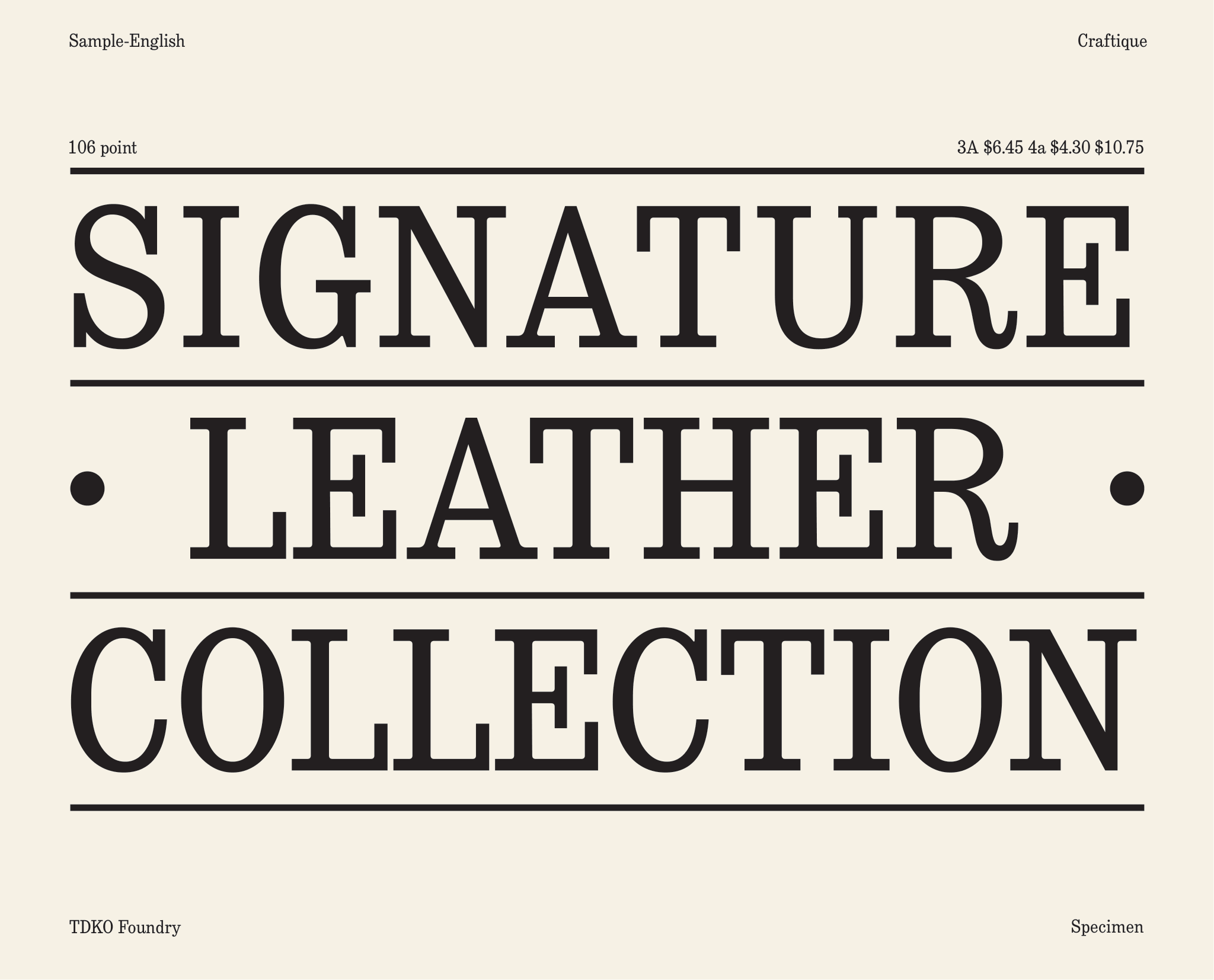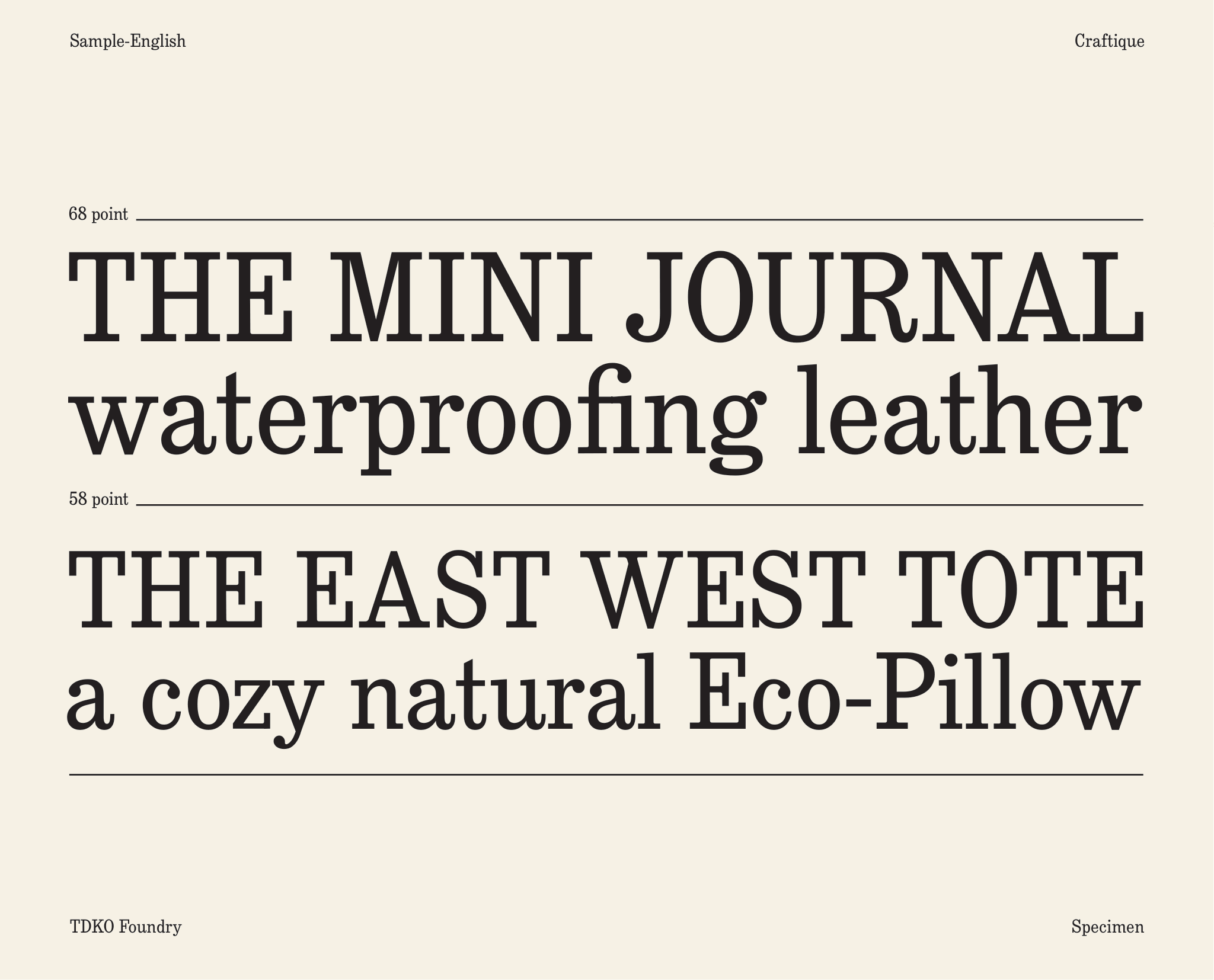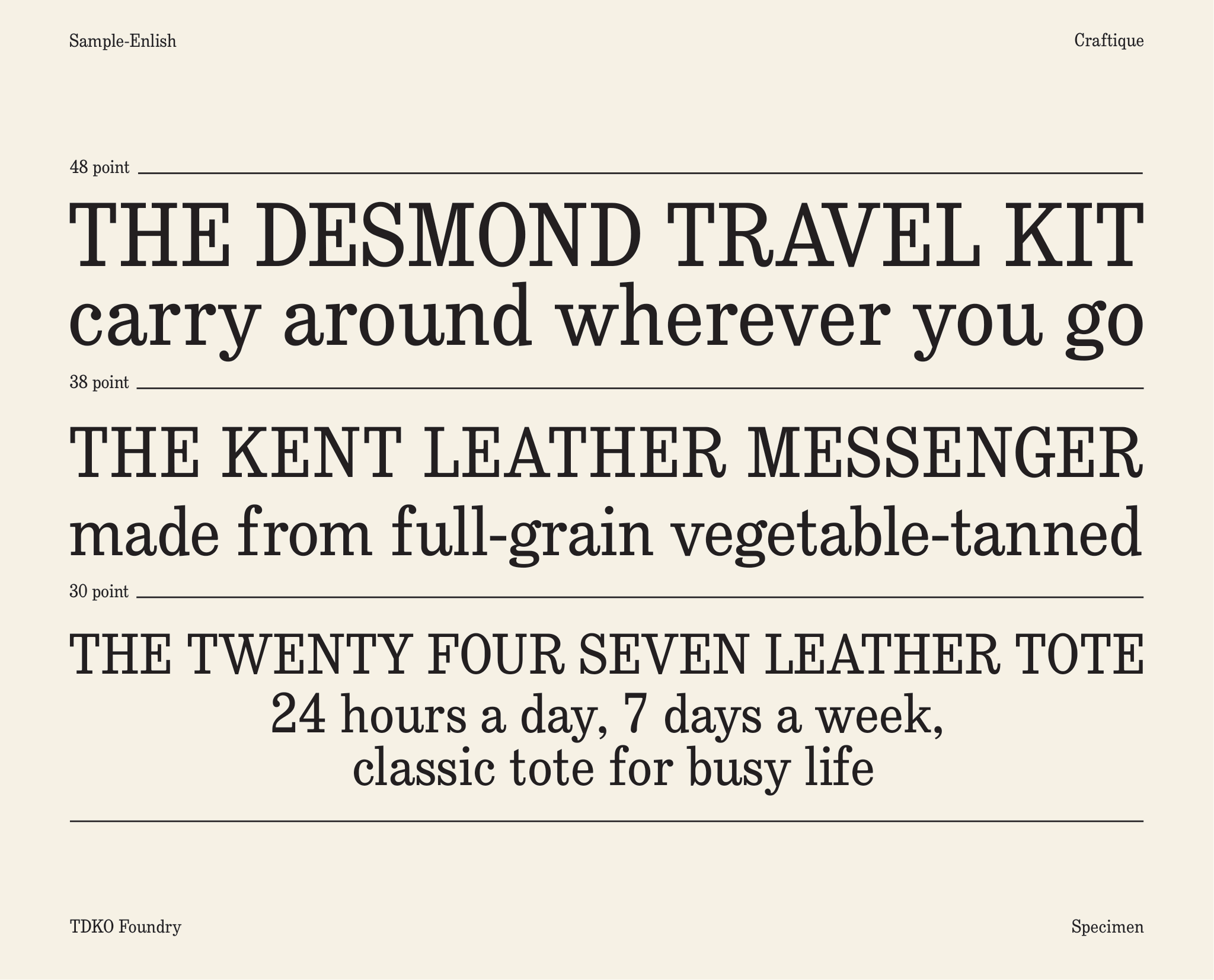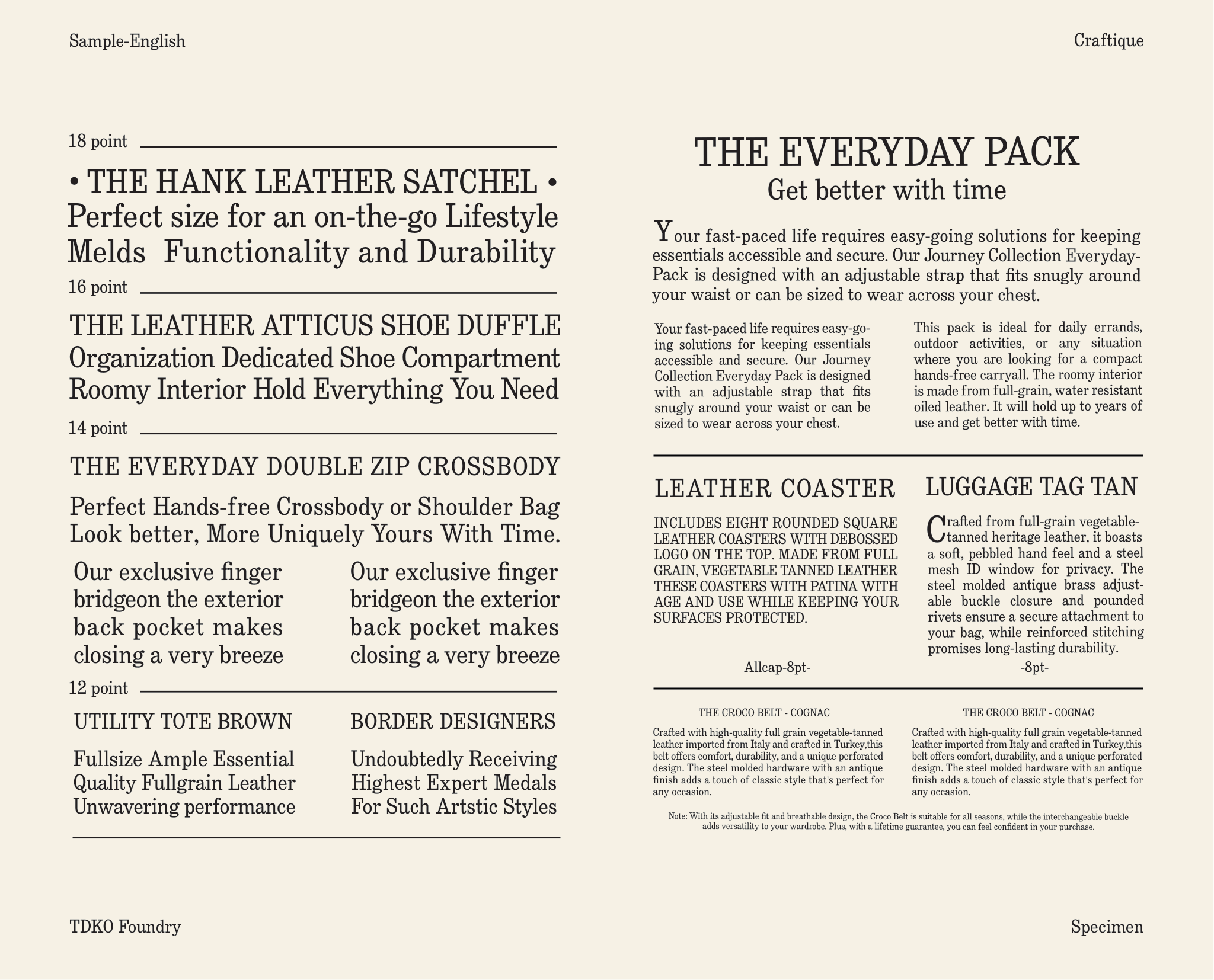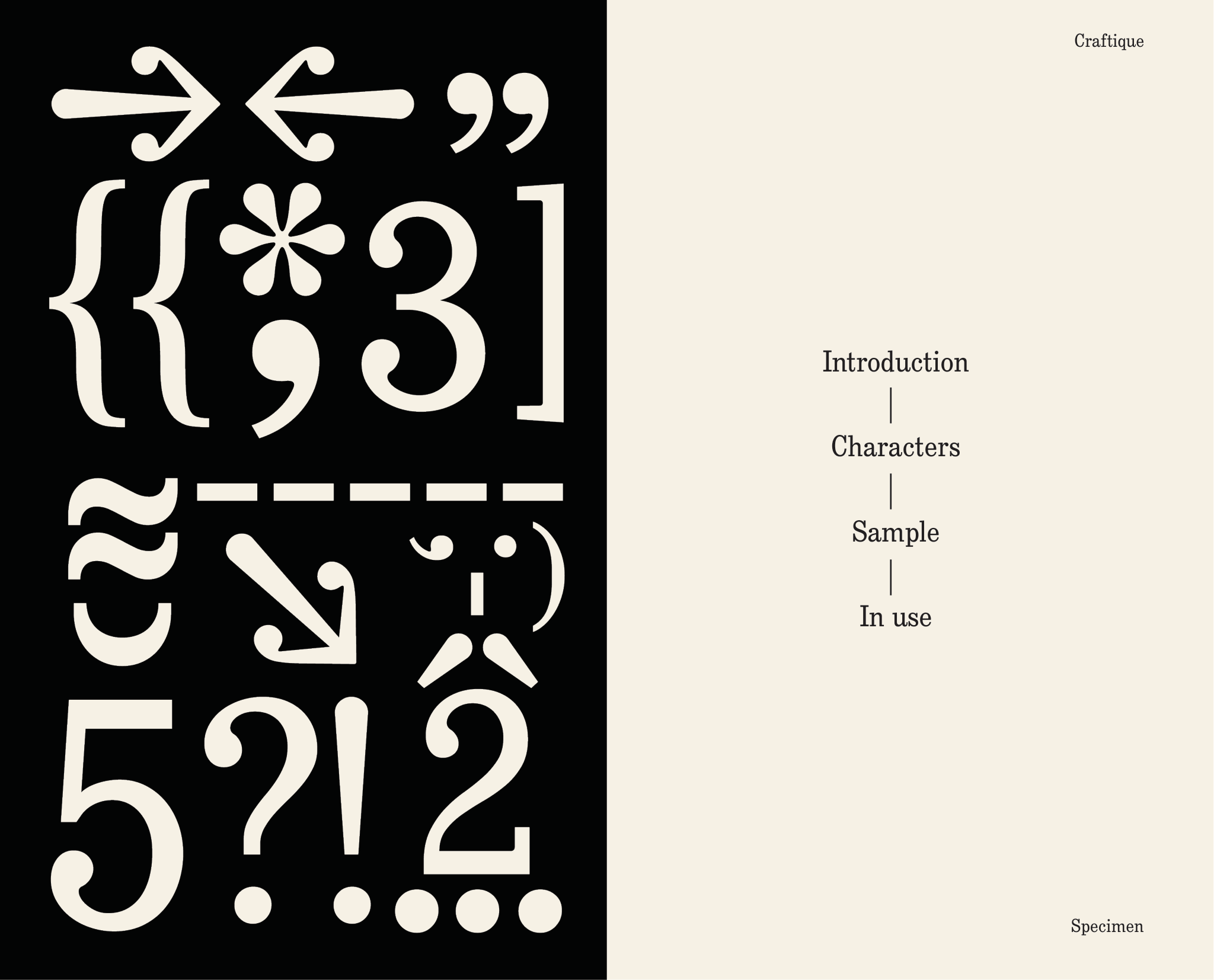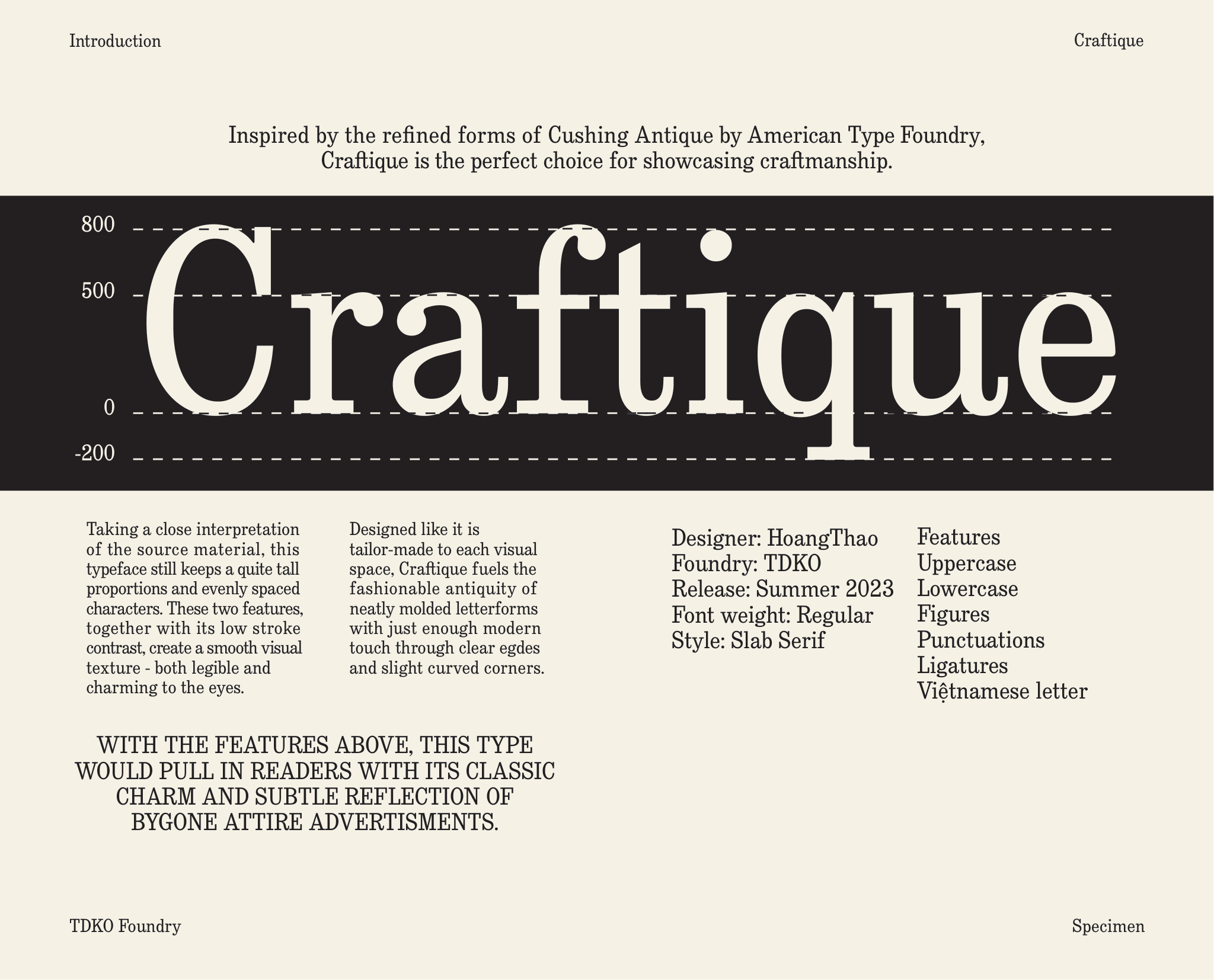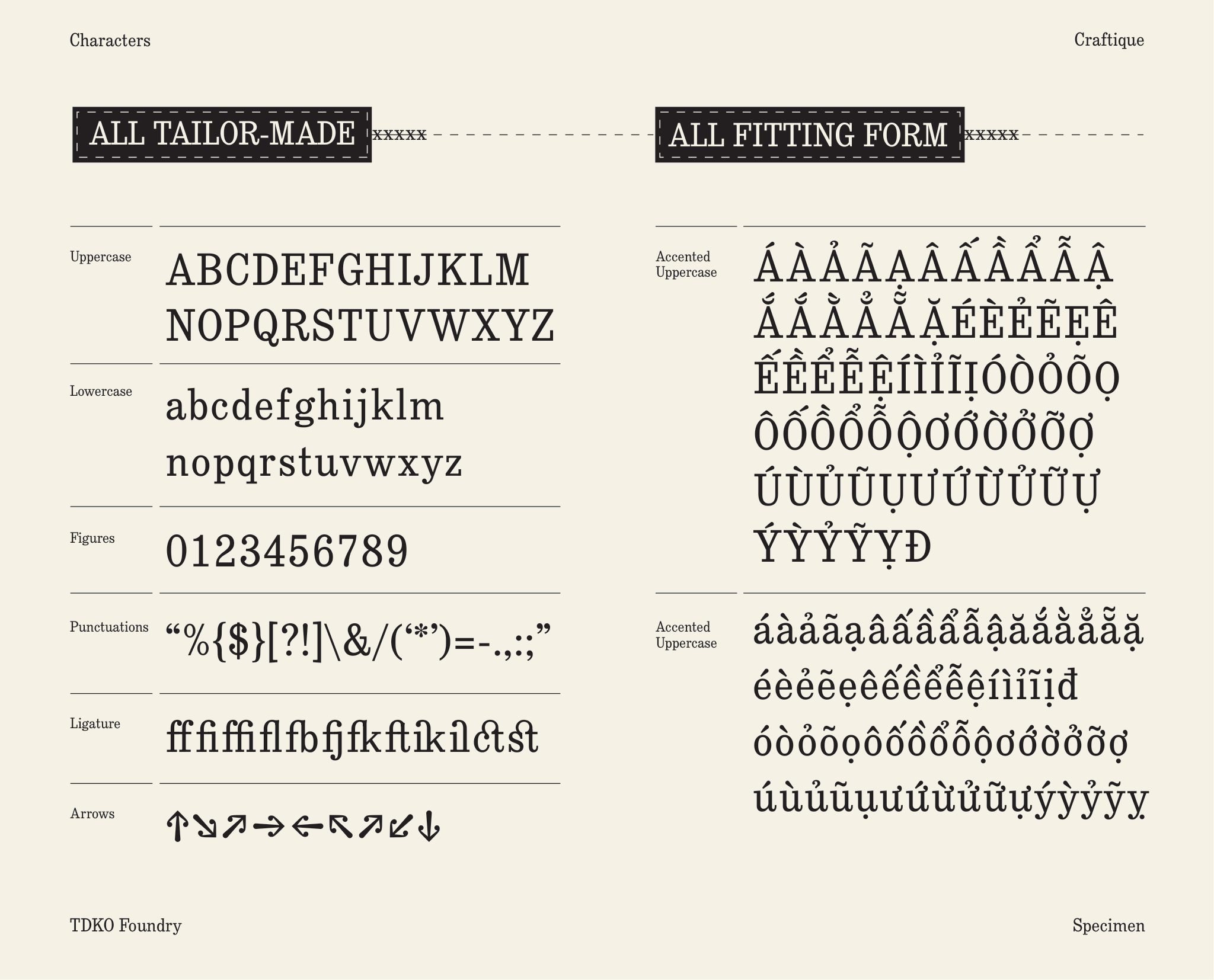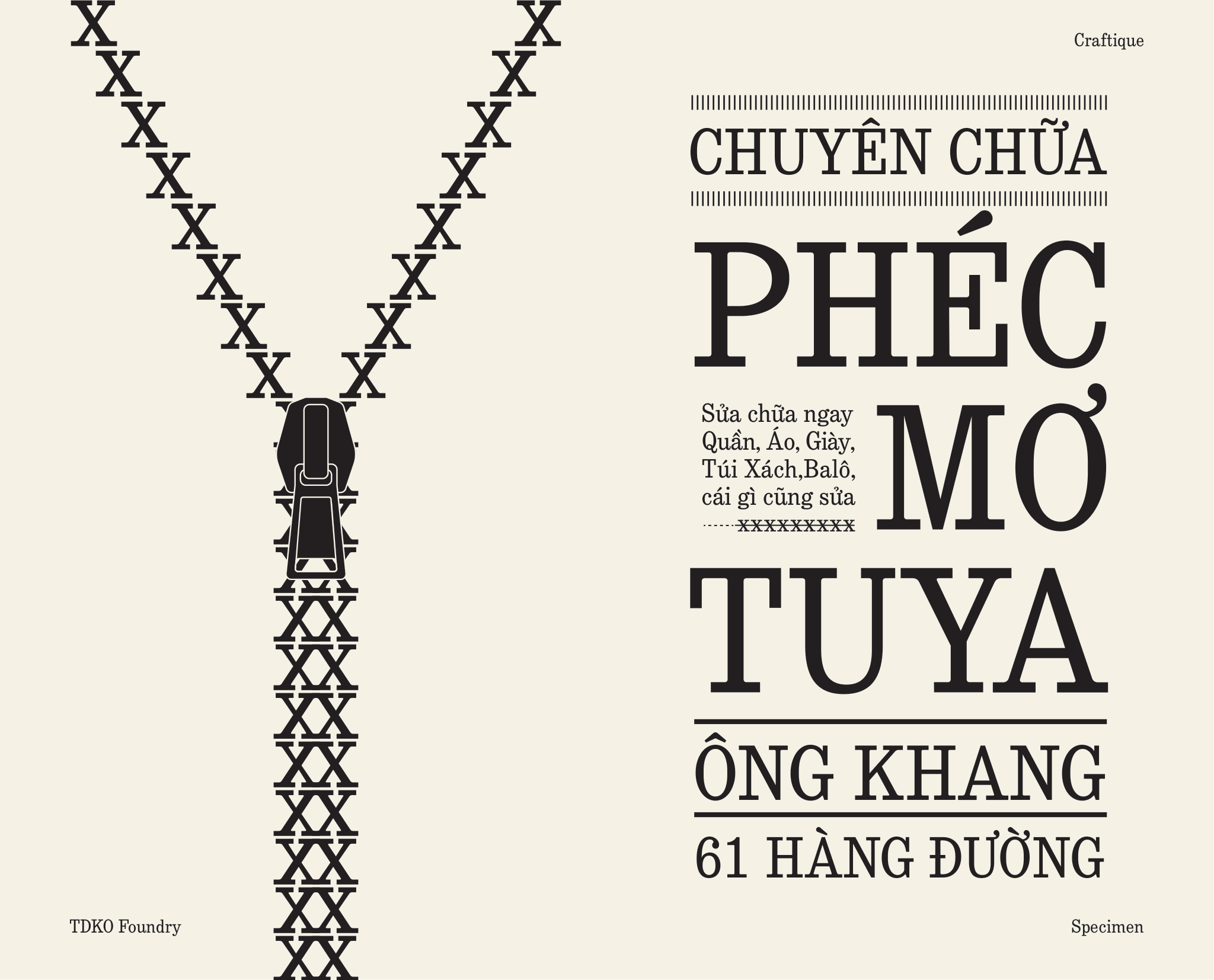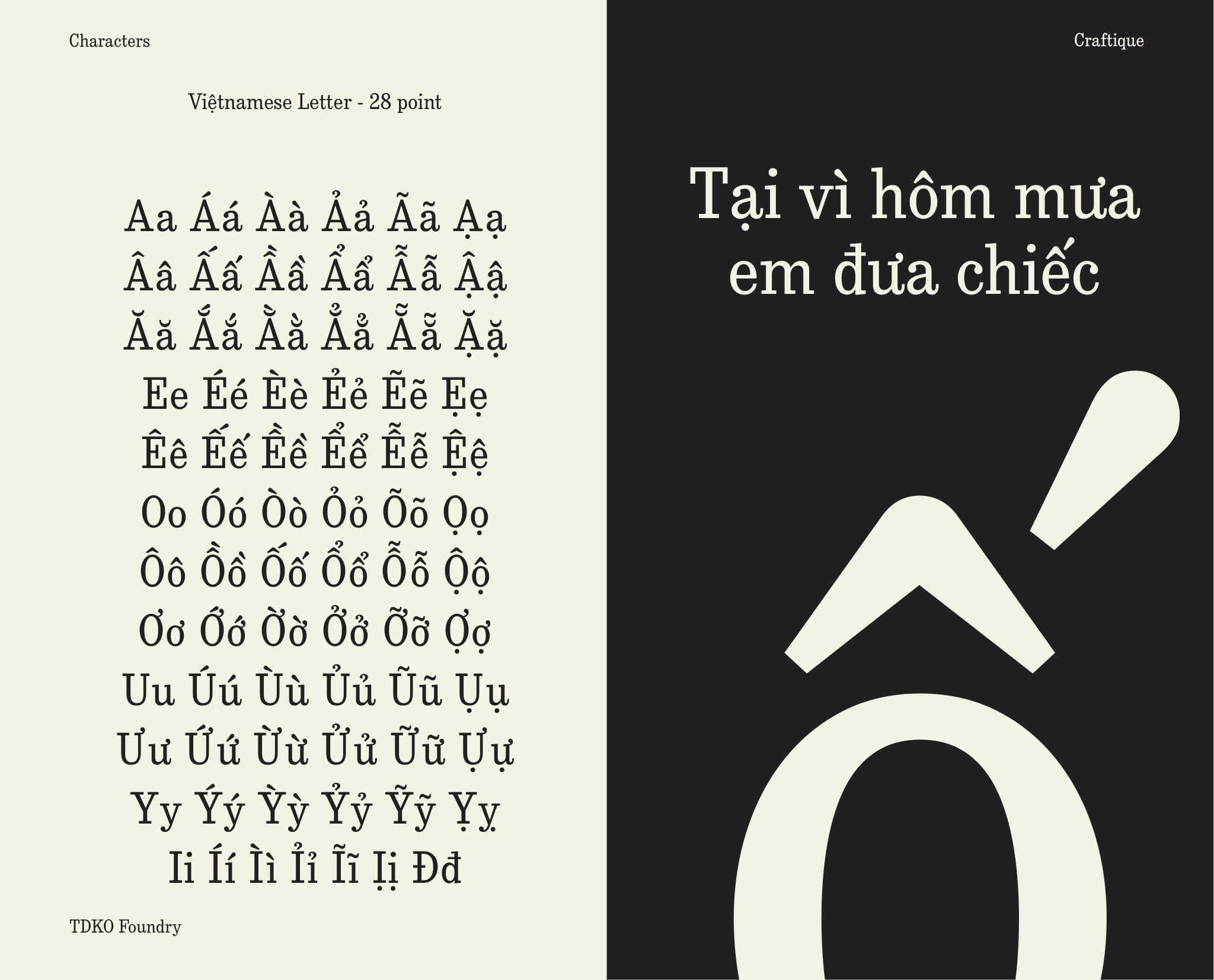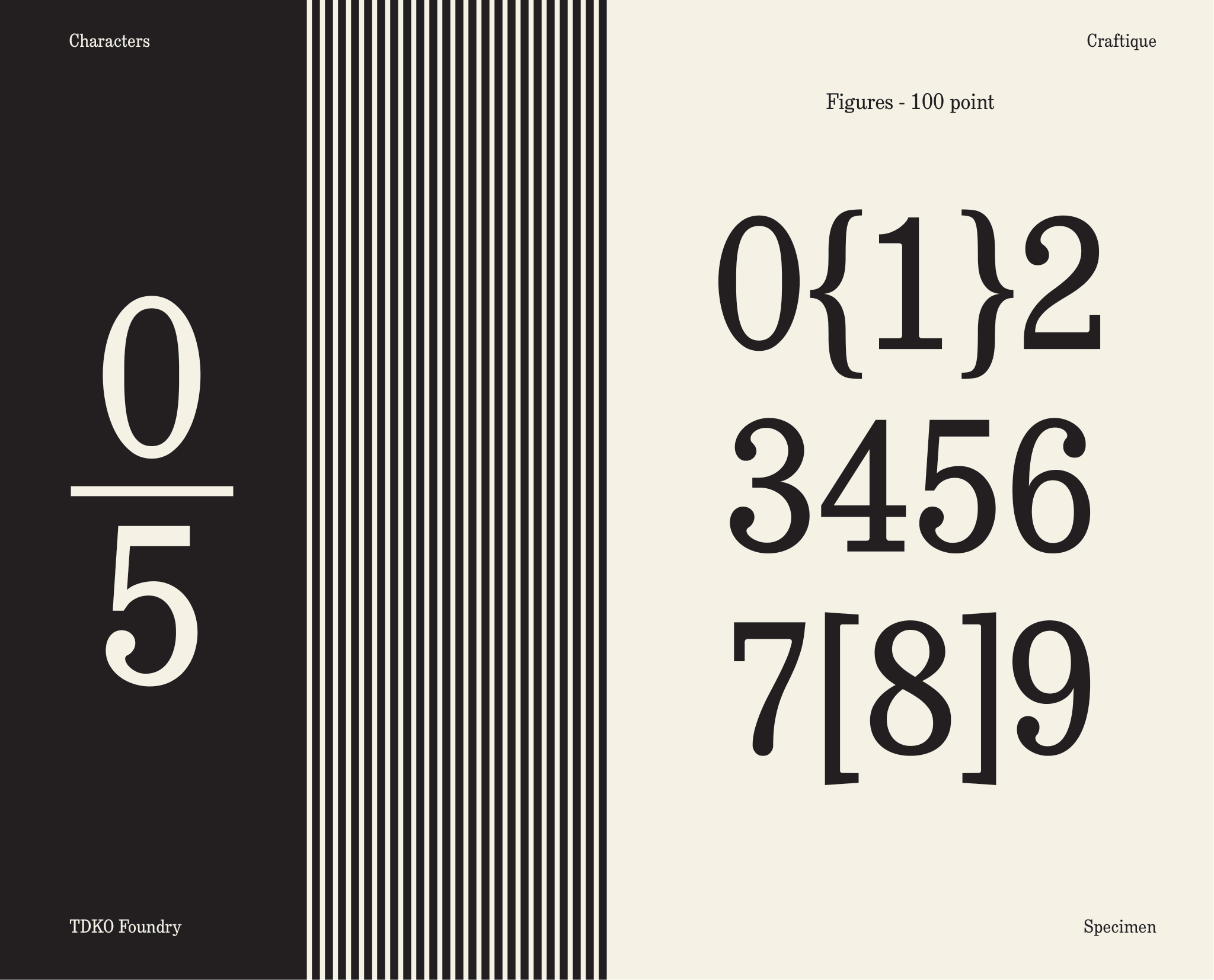
Craftique
Về Craftique: Phục dựng khá sát với bản gốc là Cushing Antique của American Type Foundry, Craftique vẫn giữ tỷ lệ khá cao và nét gần như không tương phản. Hai đặc điểm này, kết hợp với nét serif dày chắc, tạo nên phân bố mảng âm dương khá đều, vừa dễ đọc vừa dễ chịu cho mắt nhìn. Craftique khơi gợi vẻ cổ điển mang tính thời thượng của những hình dạng chữ được tạo hình gọn gàng, đồng thời vẫn có hơi thở hiện đại vừa đủ thông qua các cạnh rõ ràng và những góc bo nhẹ.
Slab Serif
Text
Hoàng Thảo
Craftique
Tailor Made
Craftique
Cushing Antique
Craftique
Đồ thủ công
Craftique
Chất liệu Tự nhiên
Craftique
Cushing Antique is a slab serif typeface released by the American Type Founders in 1902 and designed by Morris Fuller Benton.
Craftique
It belongs to the early “Antique” or Egyptian style category, which in American type terminology refers to slab serifs with relatively sturdy, rectangular serifs and a strong, utilitarian structure. Cushing Antique was part of ATF’s broader effort at the time to systematize and modernize display type for advertising, offering a more refined and readable alternative to the heavier, sometimes awkward slab serifs of the 19th century. Compared to earlier antiques, it has more balanced proportions, more consistent stroke modulation, and a clearer rhythm in text settings, making it suitable for both headlines and more continuous display copy. It also reflects Benton’s larger project of creating cohesive type families that could serve commercial printing needs with both clarity and adaptability.